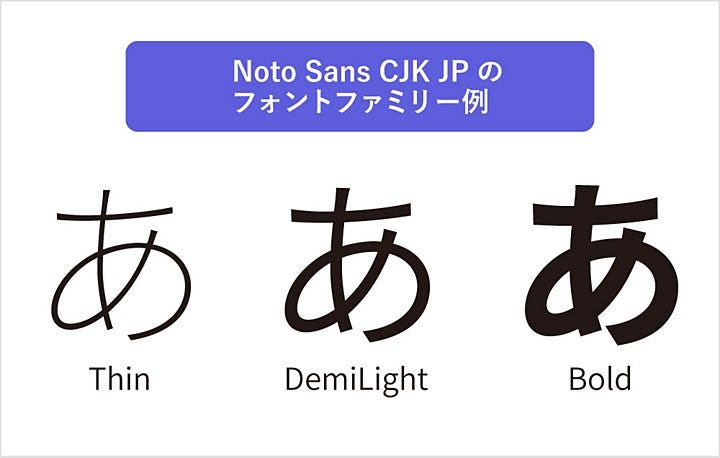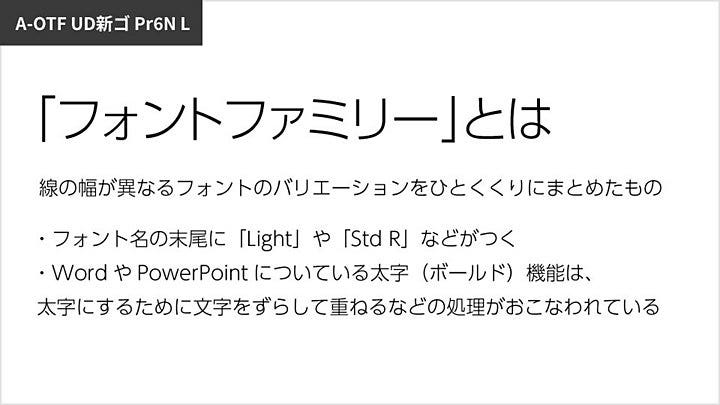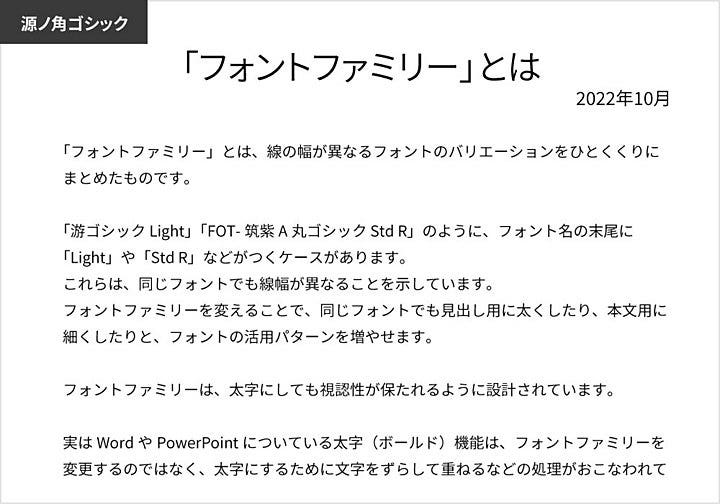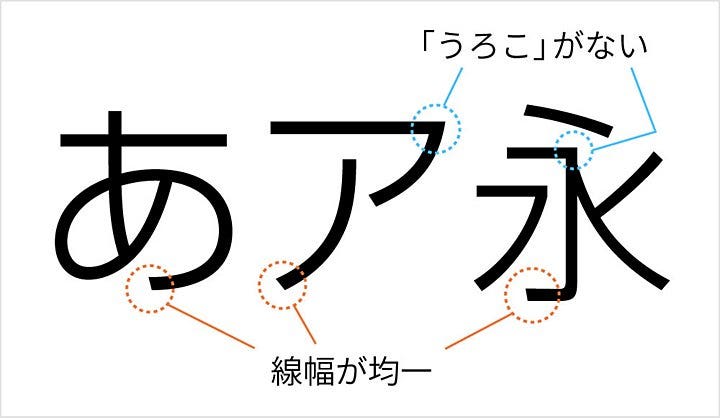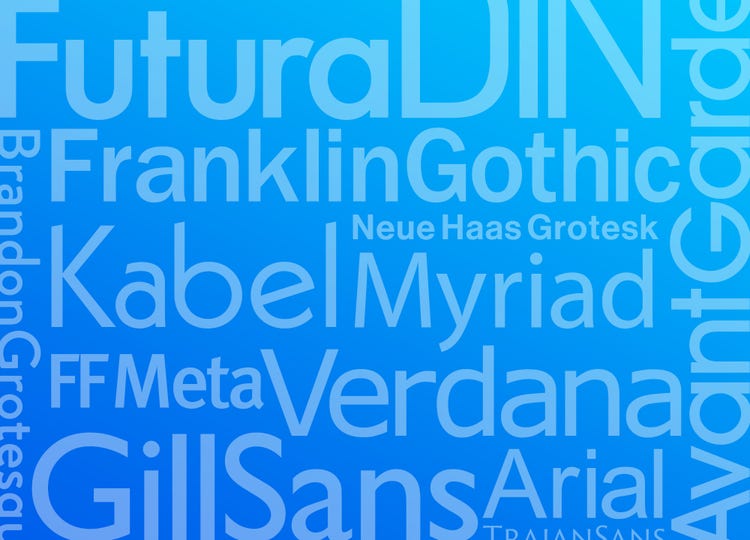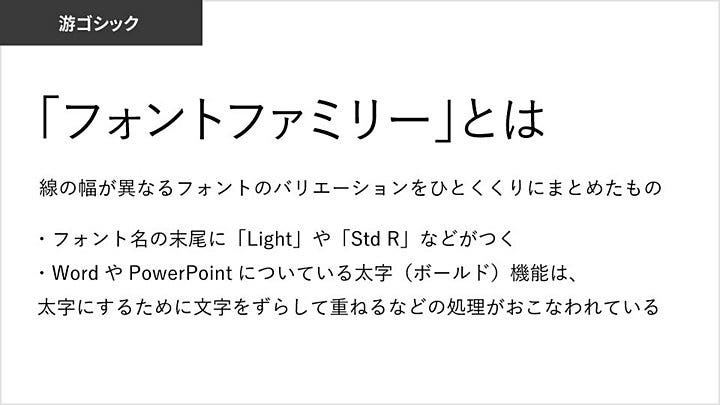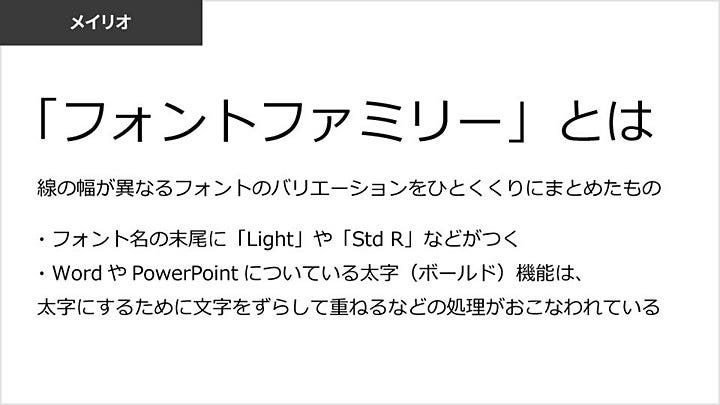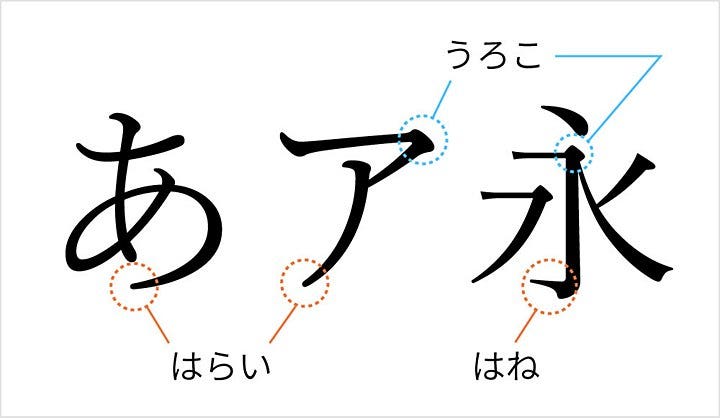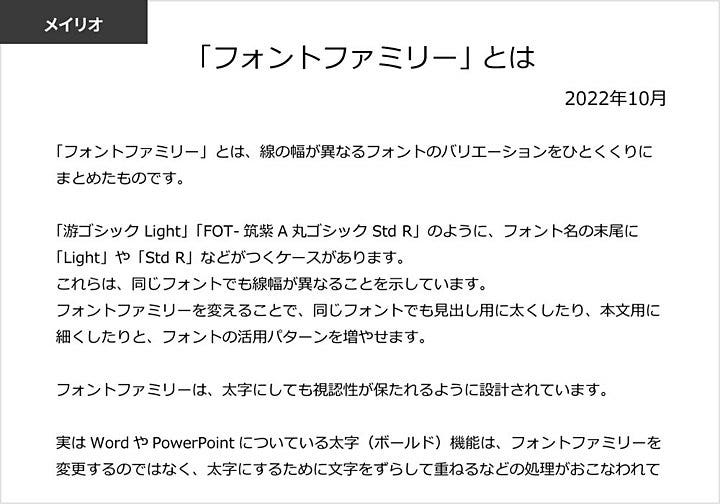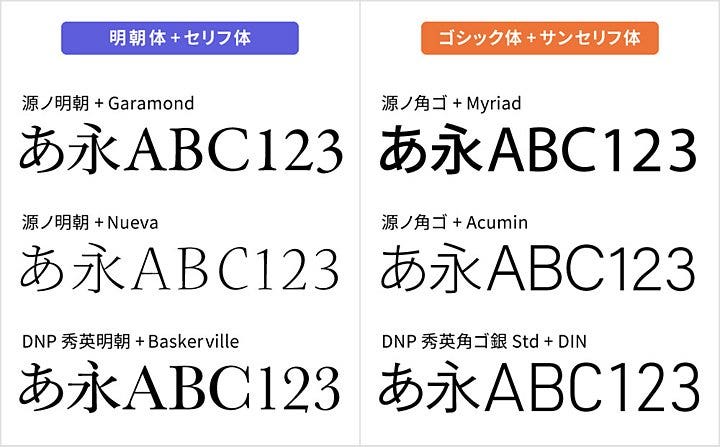
フォント(日本語・英語)の種類・選び方と定番フォントを紹介
書籍や広告、パッケージまで。
私たちが目にする制作物には、さまざまなフォントが用いられています。
今回は、ビジネスの現場で使われる定番フォントを、一挙にご紹介。
日本語・英語・数字さらには、スタンダードなものからオシャレなものまで、個人でも商用でも使えるフォントを取り上げます。
フォントの種類を知っているだけで、自分が使いたいフォントを選びやすくなります。
そうすれば、資料作成のスピードアップはもちろん、デザインの手直しを指示する際にも役立ちます。
フォントの基本知識から賢い選び方まで解説しますので、ぜひ参考にしてください。
1.フォントの種類
フォントの種類は、まず「日本語書体」と「欧文書体」に分けられます。
最初に日本語書体について解説していきます。
日本語書体(和文フォント)の種類
日本語書体とは、漢字、ひらがな、カタカナを含む書体のことです。
代表的な書体は以下の2種類です。
1.明朝体
2.ゴシック体
明朝体とゴシック体のフォント例
明朝体
明朝体は、「はね」や「はらい」などの線幅に強弱が見られたり、横線の右端に「うろこ」と呼ばれる装飾が付いている日本語書体です。
筆で書いたような線で構成され、横の線(横画)よりも縦の線(縦画)のほうが太いのが特徴です。
明朝体の線の端についている装飾「うろこ」や「はらい」「はね」
明朝体は、伝統的・上品といった印象を与えたいときによく使われます。
明朝体の代表例3つ
ゴシック体
ゴシック体は、線幅に変化がなく、明朝体に見られる「うろこ」のような装飾や、「はね」や「はらい」がありません。
ゴシック体の特徴を示した図
線に抑揚がないことから、安定感があるポップさや力強い印象を出したいときに使われるフォントです。
ゴシック体の代表例3つ
この明朝体とゴシック体の2つに加え、近年注目されているのが「UDフォント」です。
UDフォントとは
「UDフォント(ユニバーサルデザインフォント)」とは、より多くの人が読みやすいようにデザインされたフォントです。
文字の見やすさ(視認性)や見分けやすさ(判読性)をとくに重要視して作られています。
また、濁点や半濁点を大きくしたり、文字内の空間(ふところ)を広げたり、ひらがなの「はね」などをなくしシンプルにするなど、可読性を高めるための工夫が施されています。
UDフォントではない「ニューロダン-DB」とUDフォントである「UD角ゴ_ラージ-DB」の違い
近年、UDフォントは学校の教科書や道路標識、駅の案内板などに採用されることが増えてきました。
多くの人に見られることを想定した資料などでは、UDフォントの使用も検討するとよいでしょう。
続いて、英数字で構成される「欧文書体」について解説します。
欧文書体(欧文フォント)の種類
欧文書体とは、英数字で構成される書体です。
大きく分けて次の2種類があります。
1.セリフ体
2. サンセリフ体
セリフ体とサンセリフ体のフォント例
セリフ体
「セリフ」と呼ばれる、明朝体のうろこのような装飾がついている書体です。
セリフ体の特徴である「セリフ」の部分を示した図
古代ローマ時代に生まれたことから「ローマン体」とも呼ばれ、最も歴史が古い書体と言われています。
伝統的な印象をもつことが多い一方、線の太さによってはモダンな印象を出すことも可能です。
セリフの形によっても、文字の印象は異なります。
セリフ体の代表例3つ
サンセリフ体
「サン」はフランス語で「ない」という意味を表します。
つまり、「サンセリフ体」とは「セリフ」という装飾がない欧文書体を指します。
日本語のゴシック体と同様に、縦線や横線、曲線の幅が均一なのが特徴です。
「セリフ」がないというサンセリフ体の特徴を示した図
ただし、サンセリフ体と一口に言っても、フォントによって線幅の太さや英数字の形に違いがあり、各フォントごとに見た人が受ける印象はさまざまです。
サンセリフ体の代表例3つ
ちなみに、欧文書体には、「スクリプト」「ブラックレター」といった書き文字を元に作られたフォントもあります。
これらのフォントは日本人にとっては可読性が低くなりやすく、ビジネス文書などでは不向きです。
もし使いたい場合は、装飾目的として使うとよいでしょう。
スクリプト体とブラックレターの特徴とフォント例
これらの書き文字をもとに作られたフォントをまとめて「カリグラフィー」と呼びます。
以下の記事では、さまざまなカリグラフィーの記事を紹介しています。
以上のように、フォントにはさまざまな種類があります。
明朝体やゴシック体以外にも、UDフォントや欧文フォントがあることを知っておきましょう。
また、フォントは線の幅によっても印象が変わります。
そこでここからは、フォントの印象を左右する線の幅を示す「フォントファミリー」についてご紹介します。
2. フォントの印象を左右する「フォントファミリー」
「フォントファミリー」とは、線の幅が異なるフォントのバリエーションを一括りにまとめたものです。
「游ゴシック Light」「FOT-筑紫A丸ゴシック Std R」のように、フォント名の末尾に「Light」や「Std R」などがつくケースがあります。
これらは、同じフォントでも線幅が異なることを示しています。
フォントファミリーを変えることで、同じフォントでも見出し用に太くしたり、本文用に細くしたりと、フォントの活用パターンを増やせます。
Noto Sans CJK JPの「Thin」「DemiLight」「Bold」で表記した「あ」の文字の比較
フォントファミリーは、太字にしても視認性が保たれるように設計されています。
実はWordやPowerPointについている太字(ボールド)機能は、フォントファミリーを変更するのではなく、太字にするために文字をずらして重ねるなどの処理がおこなわれています。
そのため、印刷時には太字が潰れる場合があるため、太字を美しく見せたい場合は、太字のフォントファミリーが含まれているフォントを選ぶのがオススメです。
ではここからは、資料作成に役立つフォントの選び方と、オススメのフォントをご紹介します。
3.フォント選びの3つのポイント
資料作成時のフォント選びは、以下の3つのポイントを参考にしてください。
1. 長文には、適度な細さの明朝体かゴシック体を用いる
2. 誤読しやすいフォントは避ける
3. ポピュラーなフォントを選ぶ
【ポイント1】長文には、適度な細さの明朝体かゴシック体を用いる
長文においては、読み手に負担をかけないことが重要です。
文字が太いフォントや装飾が多いフォントは、字面が黒々として読み手に負荷を与えたり、文字の装飾によって読みづらくなったりする場合があります。
そのため、長文の資料を作成する場合は、装飾が少なく、適度な細さの明朝体やゴシック体がオススメです。
フォントによって長文の読みやすさが異なることを示した図
【ポイント2】誤読しやすいフォントは避ける
フォントによっては、フォントサイズを下げたときに、形が似ている文字が判別しにくい場合があります。
たとえば、数字の「0(ゼロ)」と英語の「o」、数字の「6」と「8」などの文字です。
文字を判別しにくいフォントを使うと、情報が間違った形で伝わるかもしれません。
フォントによって「o」と「a」の判別のしやすさが異なることを示した図
ビジネス資料は、誤解なく短時間で内容を伝える必要があります。
そのため、視認性が高く、読み間違いが起こりにくいフォントを選ぶようにしましょう。
たとえば本記事の冒頭で紹介した「UDフォント」も、視認性や判読性の高さを重視したフォントです。
【ポイント3】ポピュラーなフォントを選ぶ
見落としがちですが、多くの人が使っているフォントかどうかも重要な視点です。
フォントによっては、OSやデバイスに入っていない場合があります。
その場合、本来割り当てるべきフォントが見つからず、別のフォントに置き換わってしまいます。
そのため、Windows/Macにデフォルトで入っているフォントを使用するか、資料を閲覧する全員がそのフォントをダウンロードし、インストールしておくようにしましょう。
それではここから、ビジネス向けの資料作成にオススメのフォントをご紹介します。
4.ビジネス向けの資料作成にオススメのフォント
ビジネスシーンでは、Wordで文章を書いたり、PowerPointでスライド資料を作成したりすることが多いでしょう。
そこで、ドキュメント資料やプレゼン資料に適したフォントをご紹介します。
なお、Windows、Macへの標準搭載の有無は、2022年10月時点での情報です。
1.ドキュメント資料にオススメのフォント
長文のドキュメント資料では、以下の2つのポイントを意識してフォントを選びましょう。
1. サイズを小さくしても、文字が潰れにくいか
2. 文字を並べた際、文字間にゆとりがあるか
これらを意識したフォントには、たとえば以下の5種類があります。
1. 游明朝
2. 游ゴシック
3. メイリオ
4. 源ノ明朝
5. 源ノ角ゴシック
それぞれ具体的なフォントの画像も交えて、特徴を見ていきましょう。
1.游明朝
ウロコに丸みがあり、柔らかな印象が特徴のフォントです。
かっちりとした印象を与え、文章の格調高さを感じさせてくれます。
Windows、Macに標準搭載されています。
(Macでは「游明朝体」が該当します)
游明朝で組んだ長文の例
2.游ゴシック
字面が小さめで文字間にゆとりがあるため、小さなサイズで使っても一字一字の識別性が高いのが特徴です。
Windows、Macに標準搭載されています。
(Macでは「游ゴシック体」が該当します)
游ゴシックで組んだ長文の例
3.メイリオ
丸みのある書体ながら、カッチリとした雰囲気も感じさせるフォントです。
やや幅広なつくりになっており、モニター画面でも紙面上でも視認性に優れます。
Windowsに標準搭載されています。
メイリオで組んだ長文の例
4.源ノ明朝
GoogleとAdobeが共同開発したオープンソースフォント。
線が太めになっているため、文字が潰れにくく、柔らかい印象を与えてくれます。